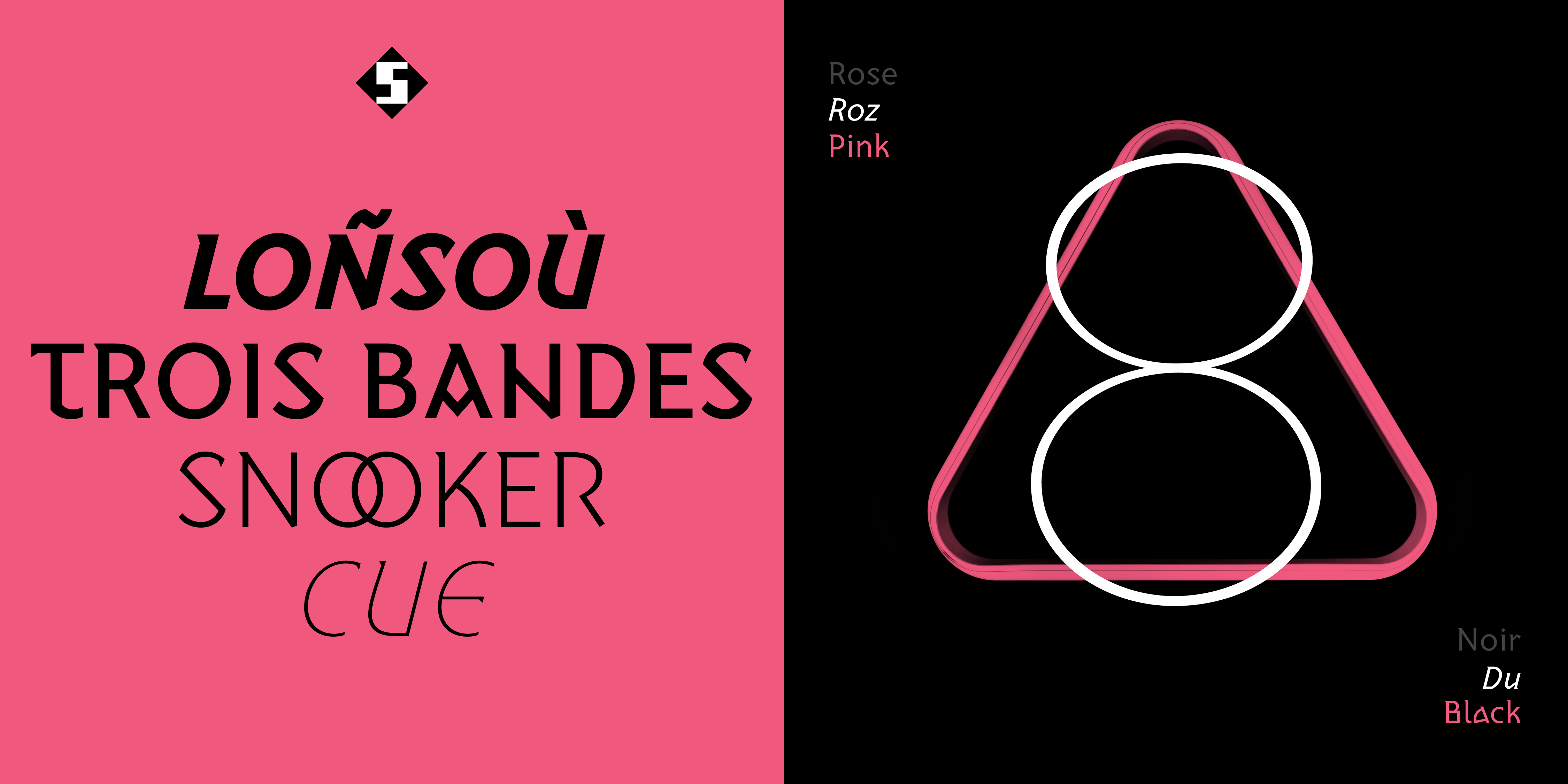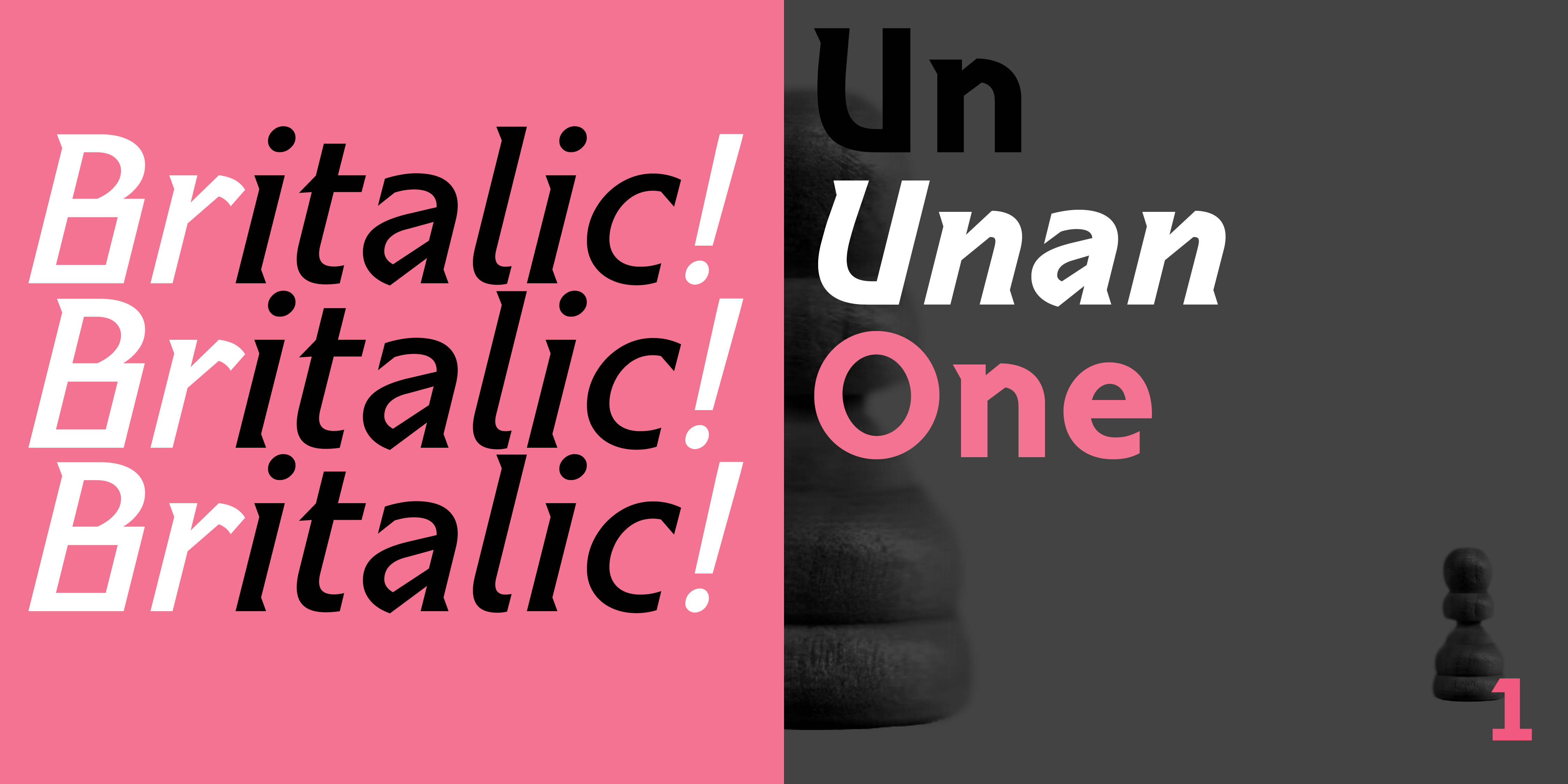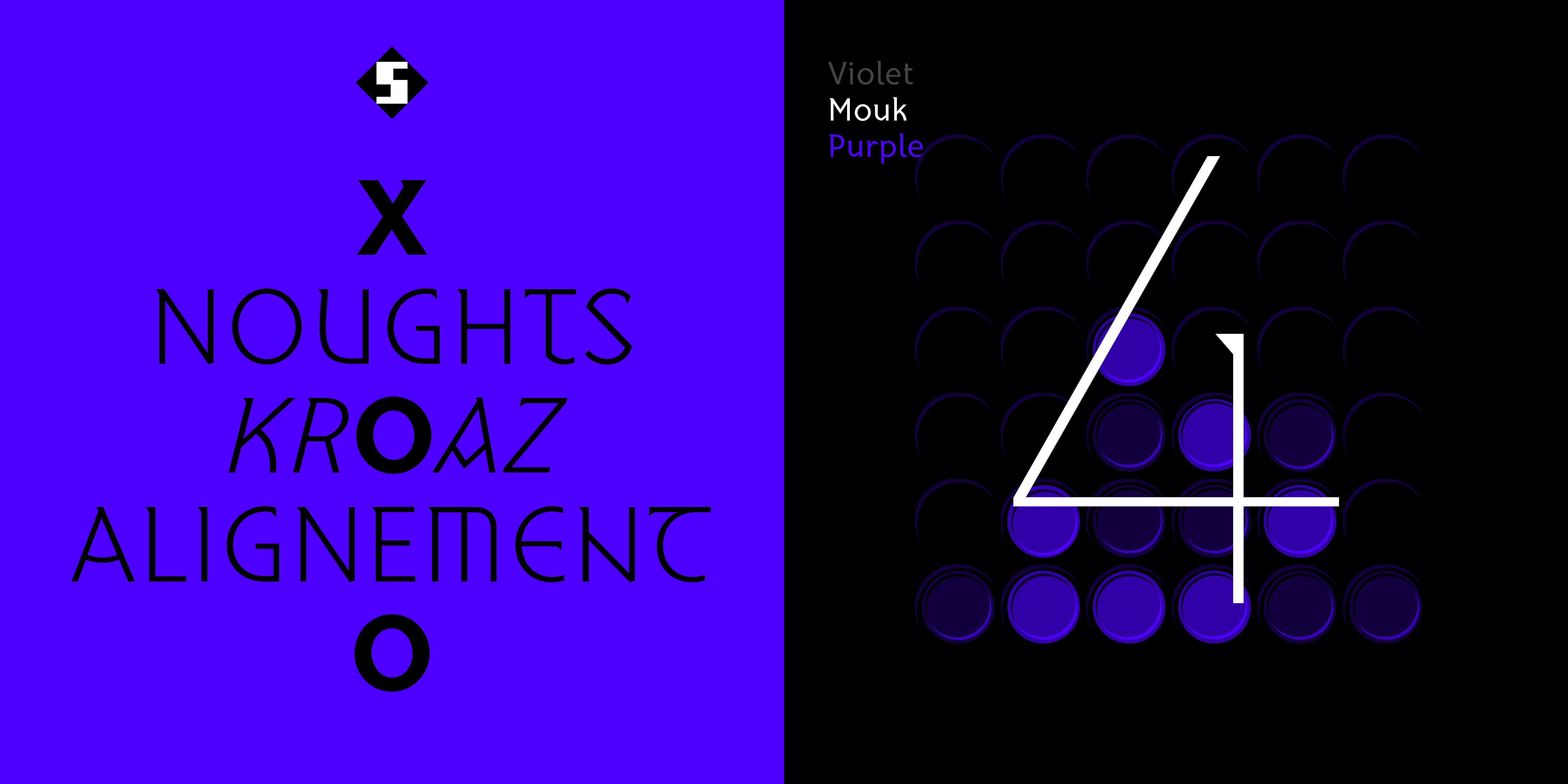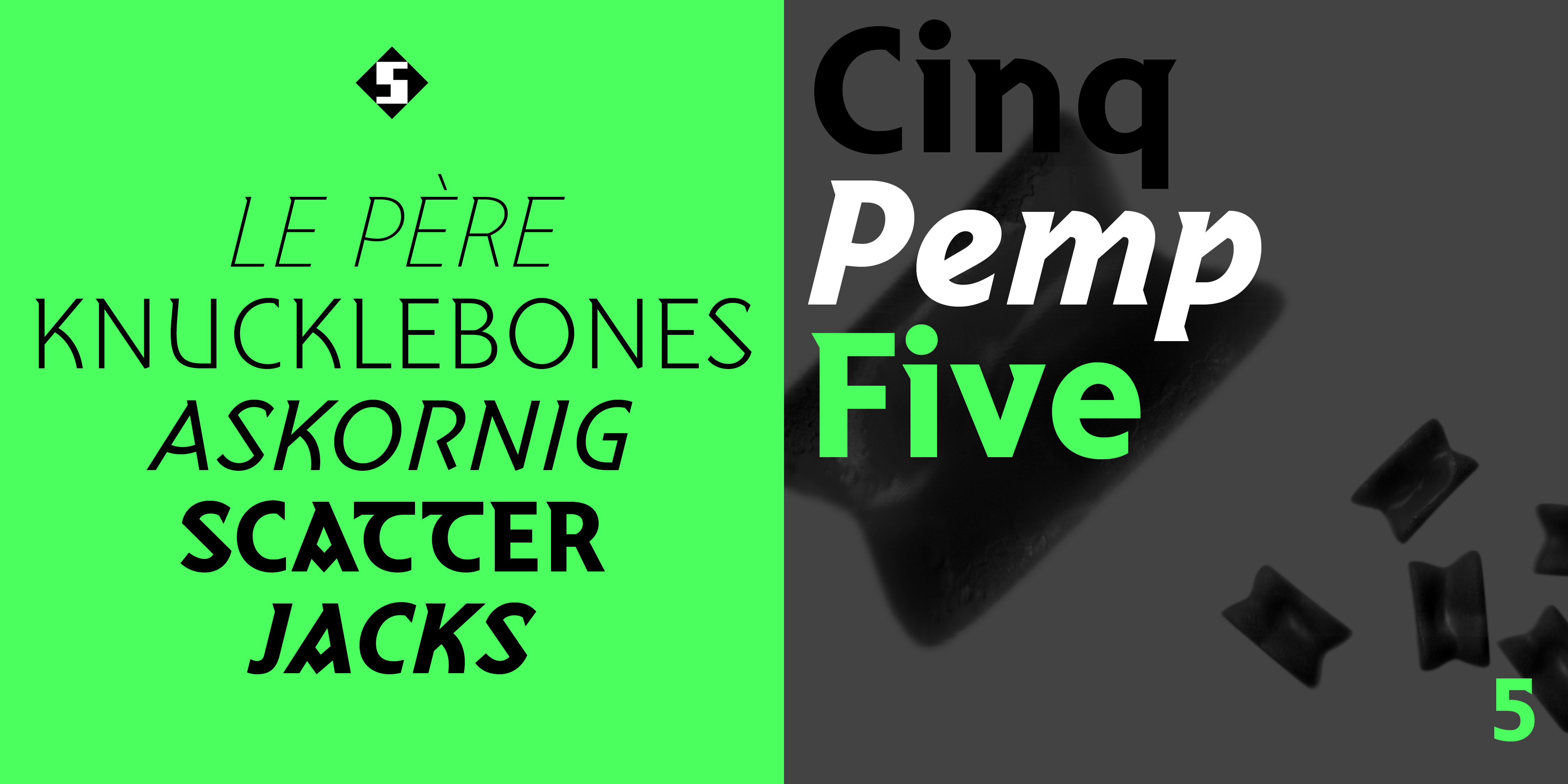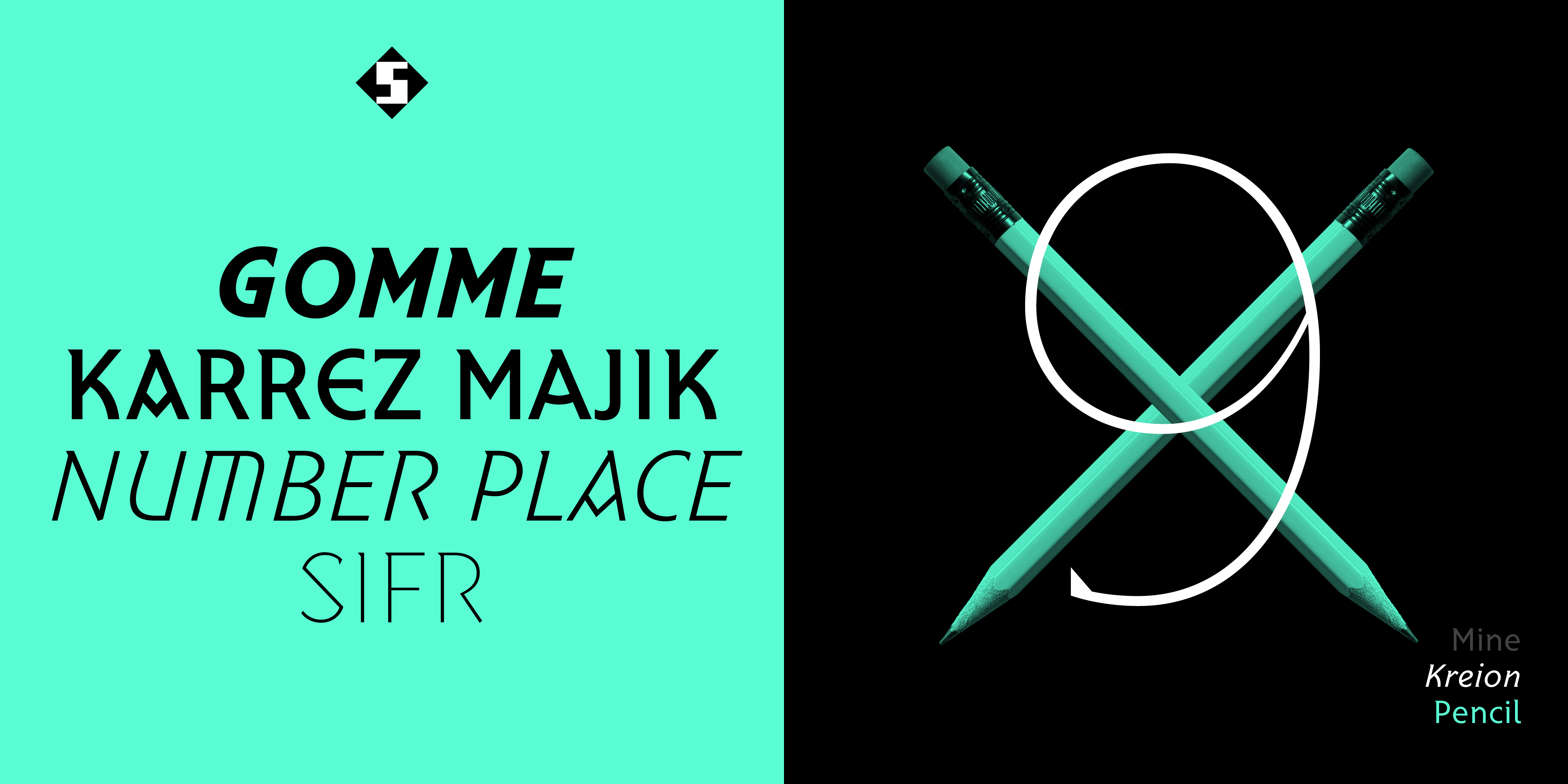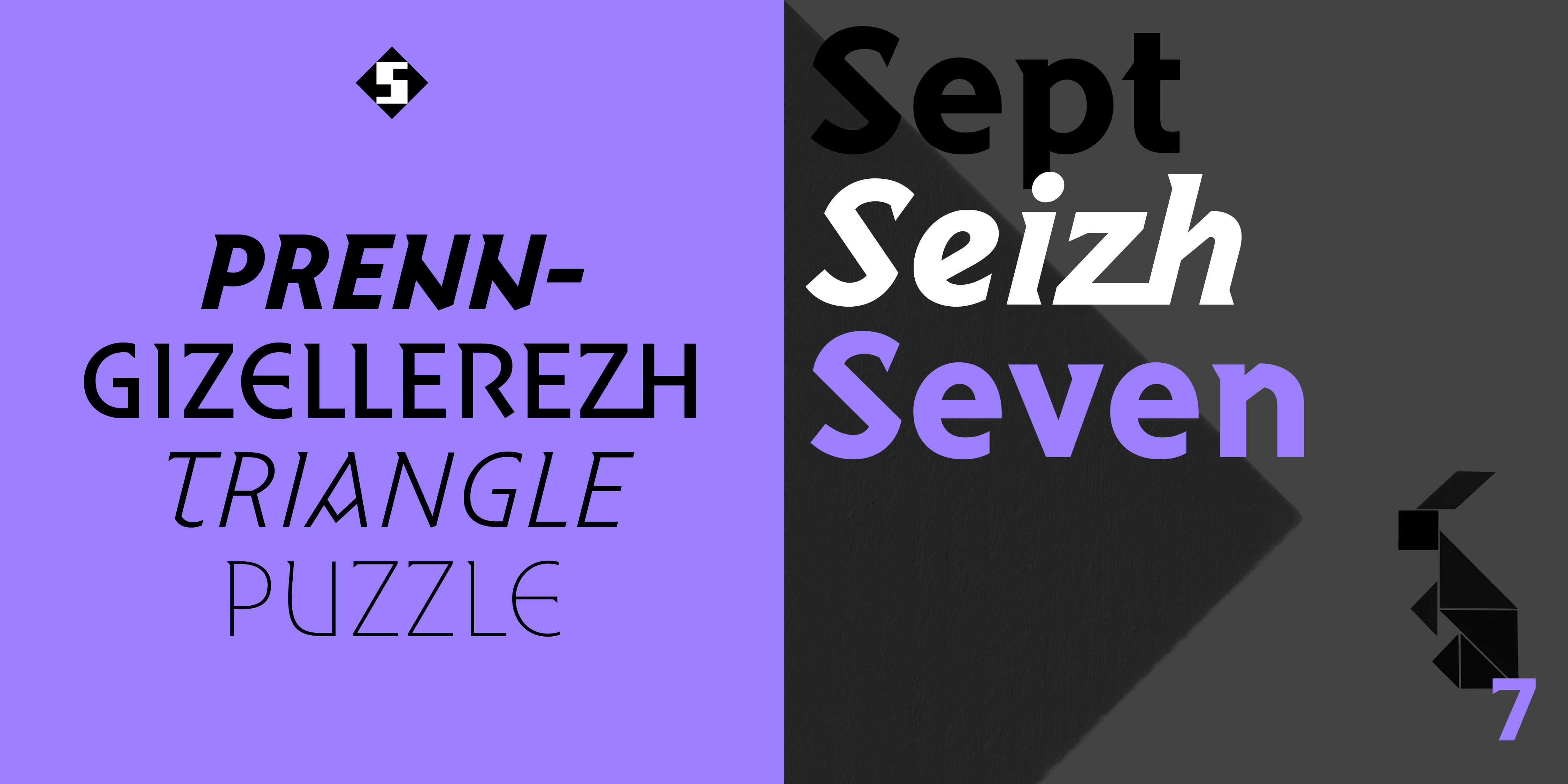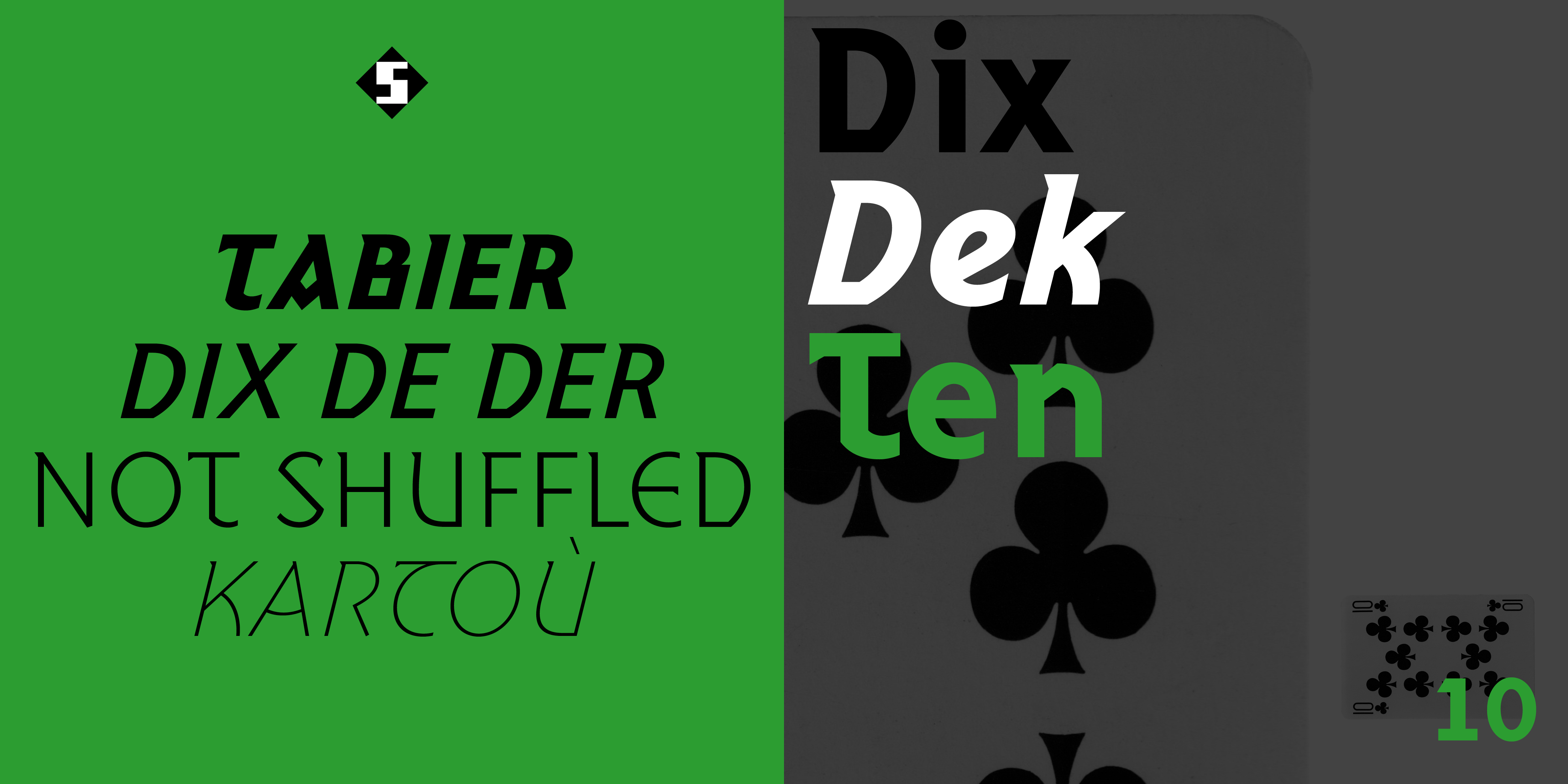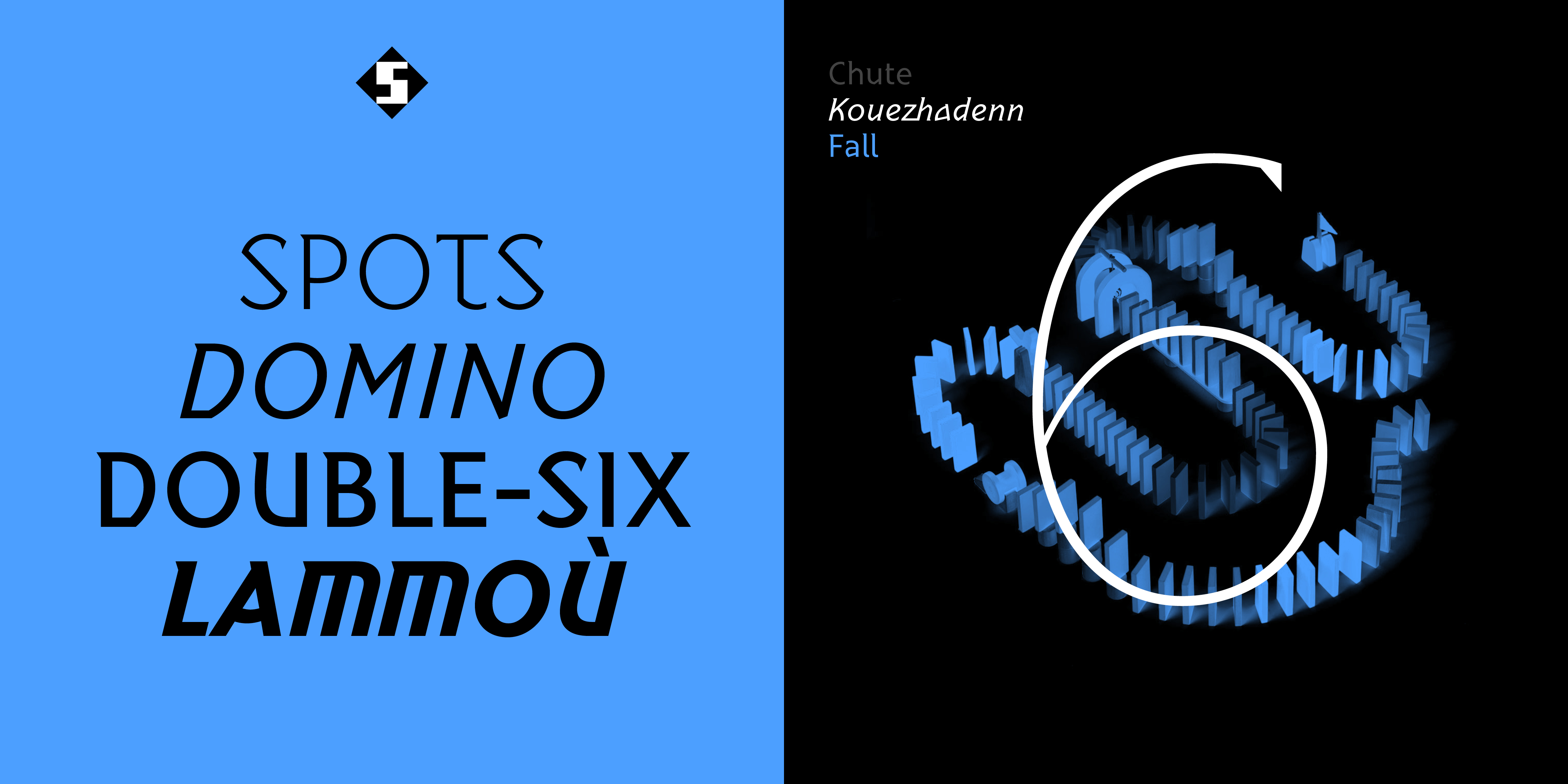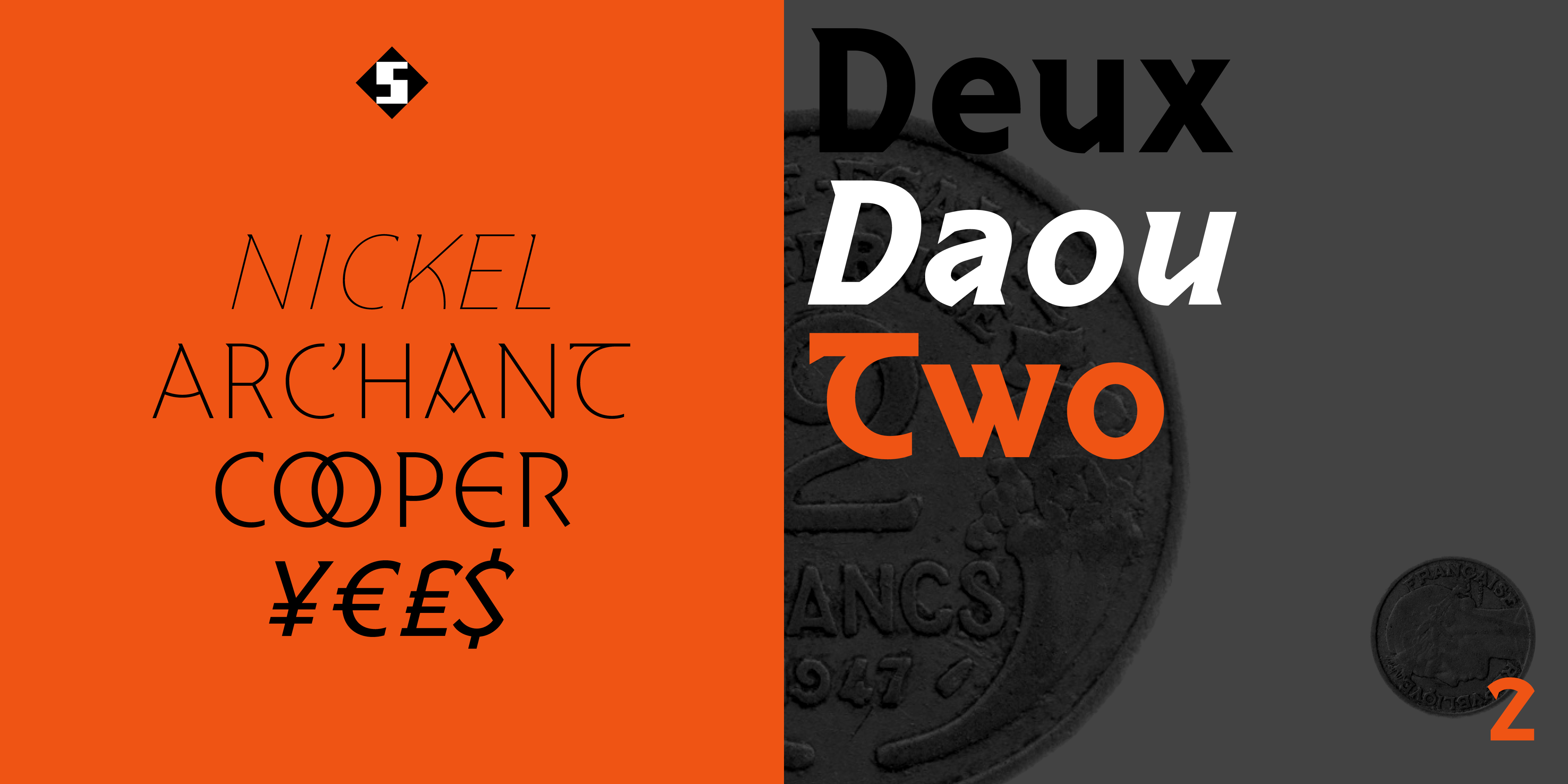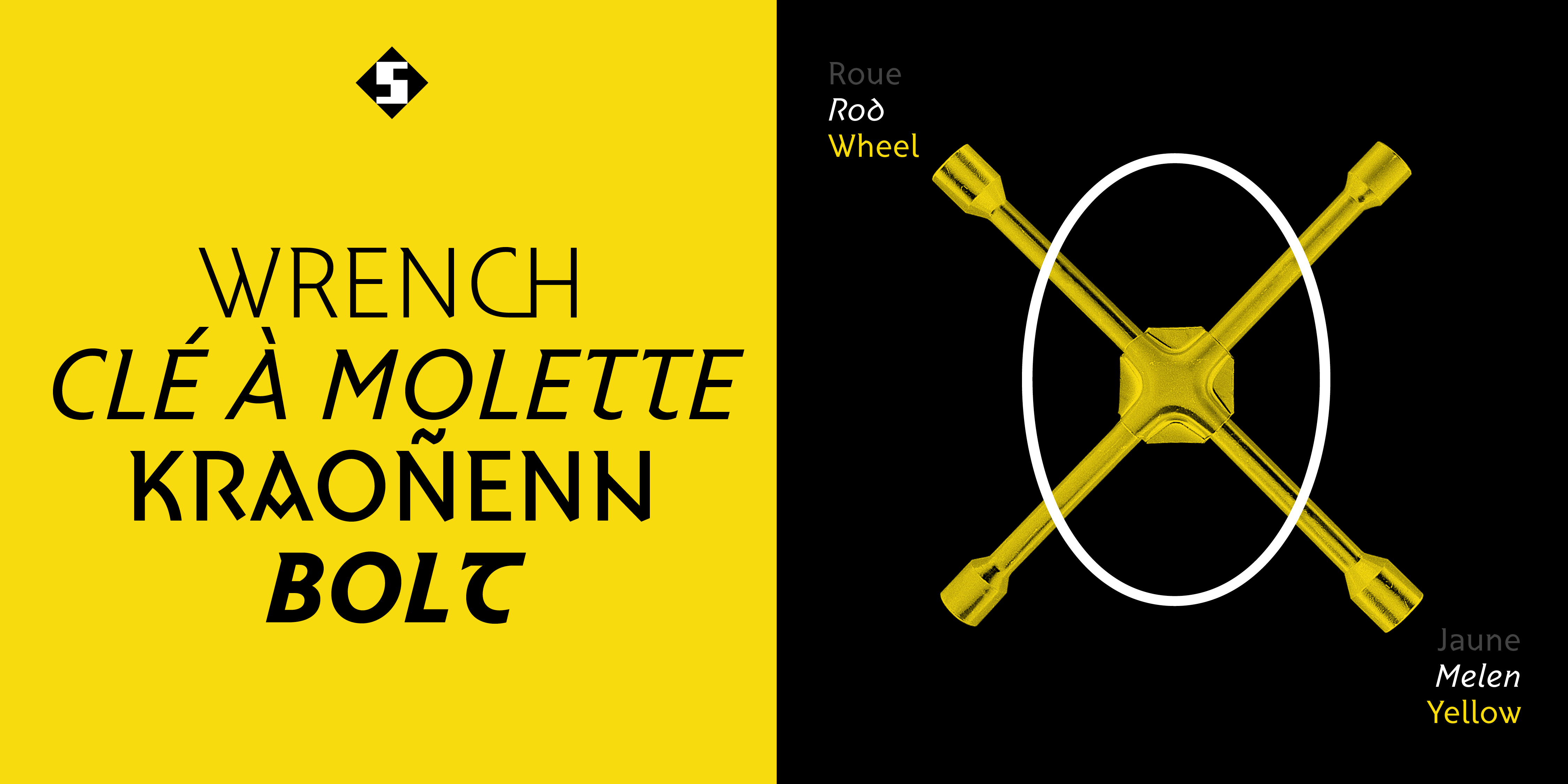
Brito Collection
Brito
Thin Extra Light Light Regular Medium Bold Thin Italic Extra Light Italic Italic Medium Italic Bold ItalicLes origines
Issu de recherches menées par Fañch Le Henaff au début des années 1990 (l’ouvrage de référence Skritur, typographie et identité paru en 1995 et le prototype de caractère Tir na Nog), le Brito est stabilisé et augmenté une première fois entre 2011 et 2013 en collaboration avec Yoann De Roeck et Malou Verlomme. Aujourd’hui, le Brito s’enrichit de nouveaux signes permettant de composer l’ensemble des langues européennes et celtiques, offre des variantes stylistiques proches des dessins originaux (plus fortement inspirés de l’onciale), le tout disponible en 6 graisses.
An orinoù
Tennet eus labourioù kentañ Fanch An Henaff (Tir na Nog, e 1995), ar Brito a zo bet stabilaet e stummoù ha kresket ar wech kentañ etre 2011 ha 2013 gant kenlabour Yoann De Roeck ha Malou Verlomme. Hiziv, ar Brito en em astenn gant sinoù nevez evit komposiñ en holl yezhoù europeat ha keltiek, en ur ginnig stiloù liesseurt tost eus an tresadennoù orin, an holl gant 6 mod-tevder.
Origins
Inherited from Fañch Le Henaff’s early work (Tir na Nog, in 1995), the Brito typeface is stabilised and increased for the first time between 2011 and 2013 in partnership with Yoann De Roeck & Malou Verlomme. Today, the Brito is fully upgraded with new glyphs allowing to support every European and Celtic languages, it also offers stylistic alternates close to the original oncial designs. It is now available in 6 weights.